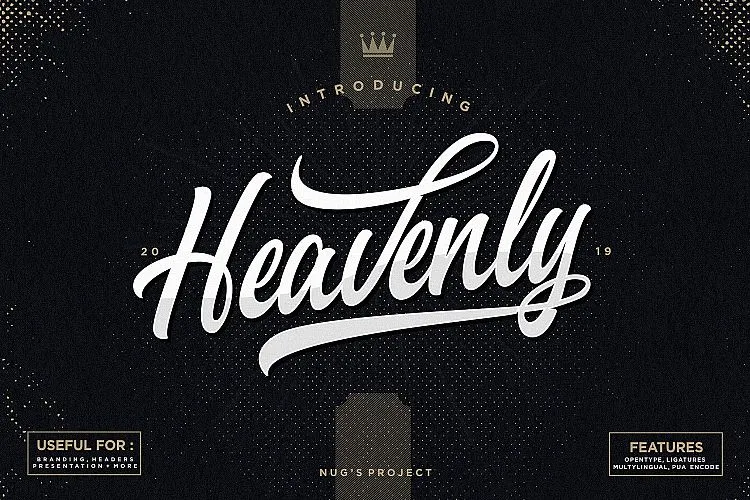
Heavenly Script Typeface é uma tipografia script criada pelo designer Nug’s Project, com um estilo que remete à escrita chinesa ou japonesa e seu formato curvilíneo é tão atraente quanto versátil. Esta fonte de script possui personalidade e abrange uma variedade de usos, desde identidades de marca, cartazes e marcas publicitárias até mensagens atrativas em ambientes digitais. Com seus caracteres fluidos e elegantes, Heavenly Script Typeface é perfeito para usar em múltiplas aplicações. Suas alternativas e combinações variadas permitem que você personalize o estilo da fonte conforme necessário para atender aos requisitos de seu projeto, seja ela uma marca digital ou um design de impressão tradicional. Onde quer que você use Heavenly Script Typeface, a certeza é: cada mensagem será entregue com personalidade e destaque, sem dúvida um elemento imprescindível em qualquer projeto gráfico. Seja para criar cartazes impactantes, desenvolver identidades de marca ou apenas aumentar o brilho de suas mensagens, Heavenly Script Typeface tem tudo que você precisa. Com seu estilo único e sua versatilidade multifuncional, esta fonte oferece um design elegante que se adapta a qualquer necessidade do designer moderno.